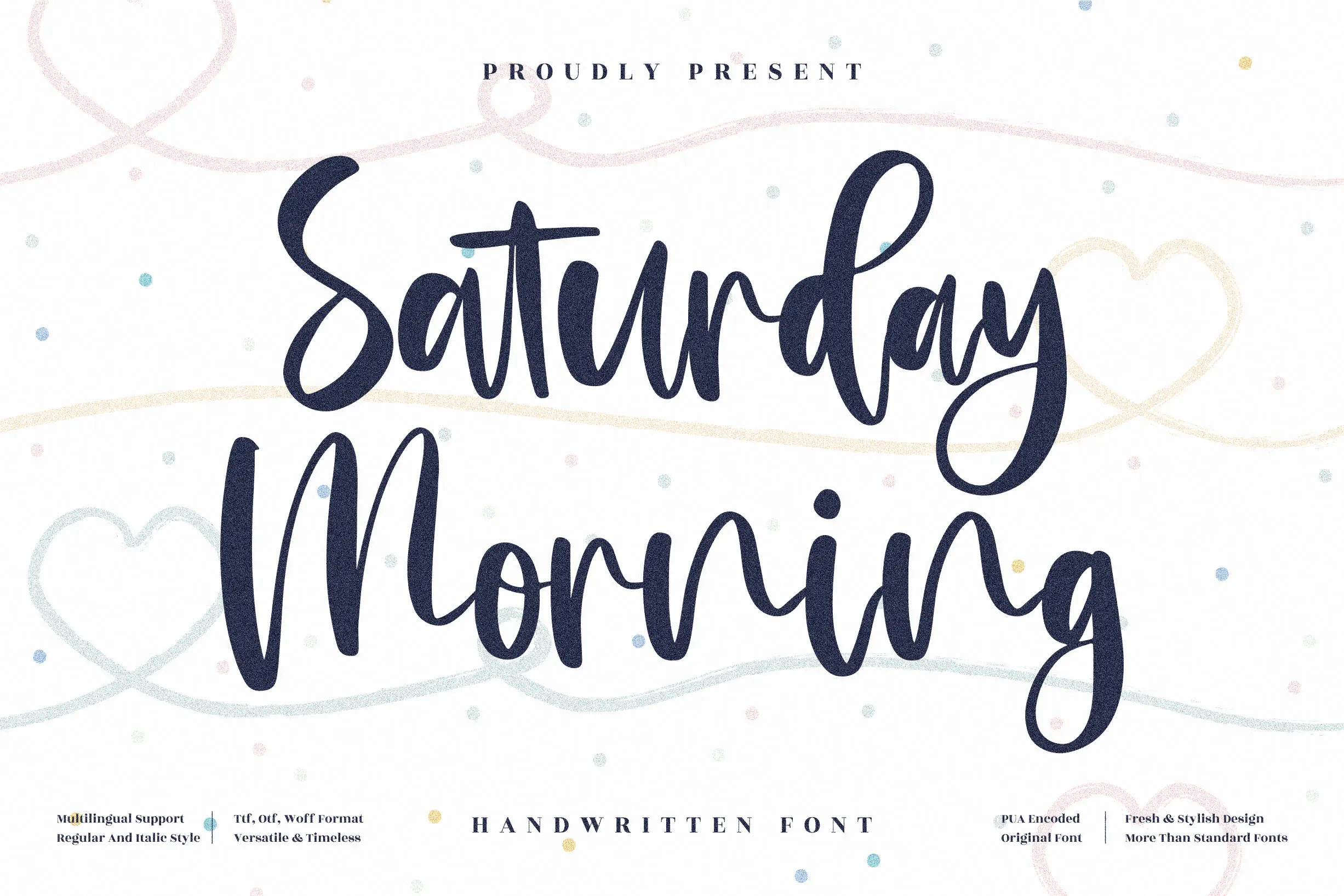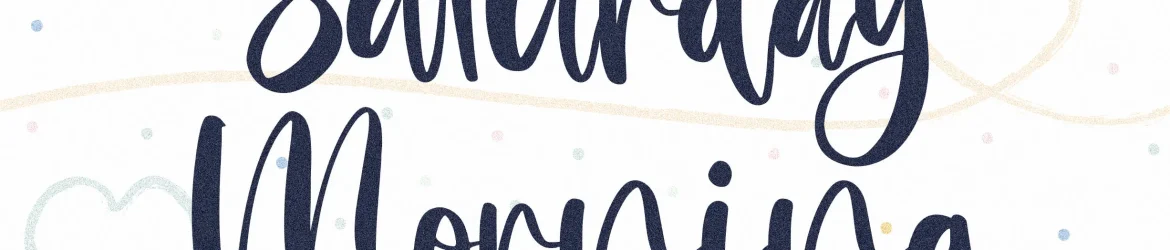
Saturday Morning Font – Download Grátis
Esta é uma fonte escrita a mão projetada para qualquer projeto que precise de um toque autêntico e único. É perfeita tanto para trabalhos mais formais, como logomarcas ou design de embalagens, quanto para artigos mais pessoais, como cartões de convite ou até mesmo fotografias. A perspectype Saturday Morning Font é perfeitamente adaptada para adicionar um toque autêntico e familiar a seus projetos. Ela pode ser usada em uma variedade de materiais e formatos, desde etiquetas e revistas até cartões de visita e capas de livros. Seja qual seja o seu projeto, este fonte escrita a mão adicionará um toque autêntico e único que certamente tornará seus projetos ainda mais especiais. Com sua paleta de letras suaves e elegantes, esta fonte é uma ótima opção para quem busca expressar seu trabalho com uma personalidade única. Perfeita para designers de marca e criadores de produtos, ela pode transformar qualquer projeto em um verdadeiro toque especial. Com certeza, perspectype Saturday Morning Font será um investimento valioso na sua colecão de fontes, garantindo que seus projetos sejam sempre inovadores e autênticos.